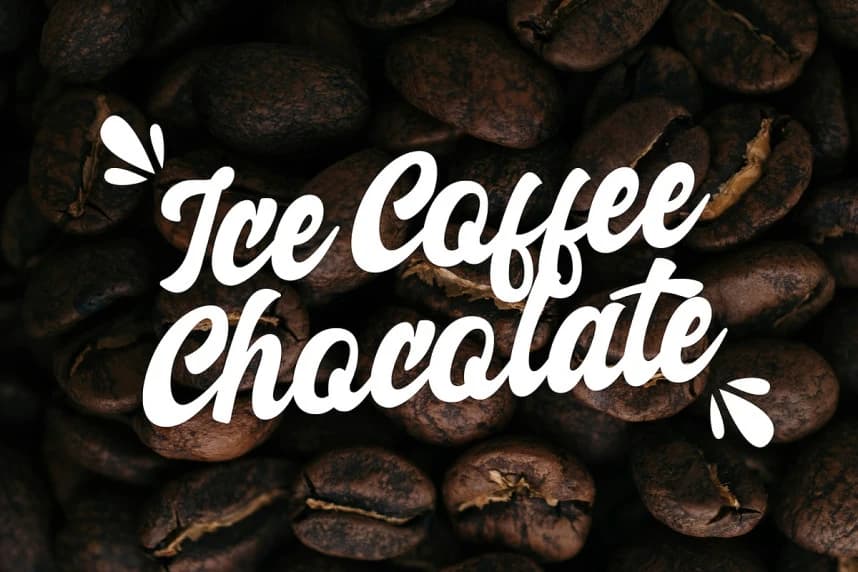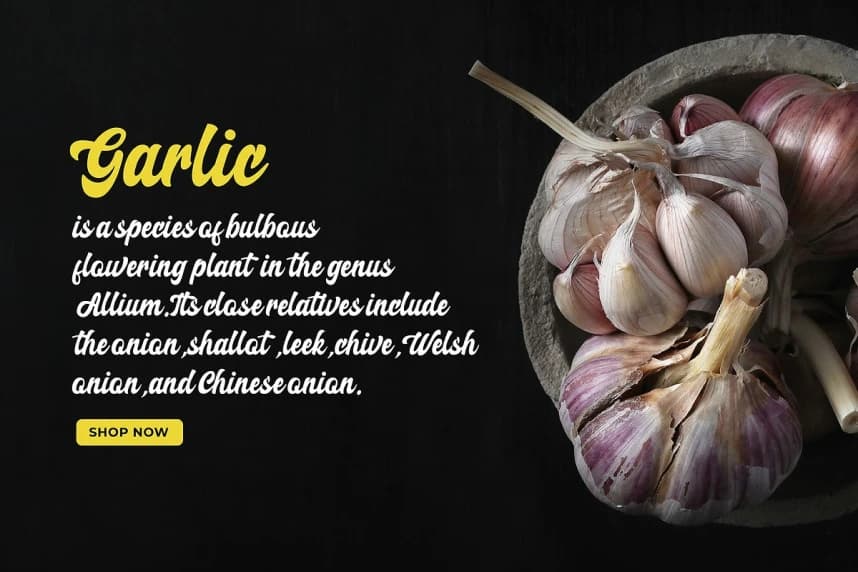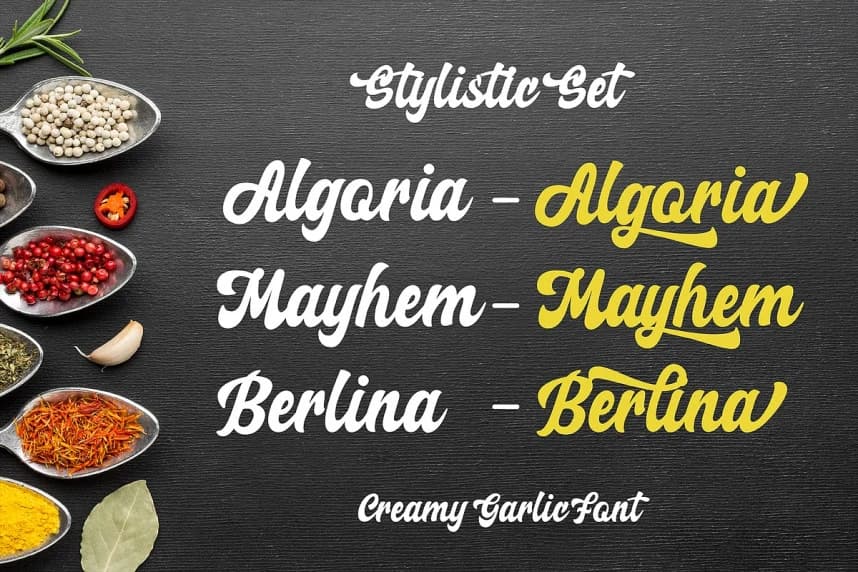
Kremalı Sarımsak Yazı Tipi
Creamy Garlic Font, zevkli ve zarif bir kalligrafik yazı tipidir. Onun zarif çizgileri ve akıcı eğrileri metninize sofistike bir dokunuş katar. Davetiyeler, kartlar veya stil ve çekiciliğin birleşimini gerektiren herhangi bir proje için idealdir.
Creamy Garlic Font, zevkli ve zarif bir kaligrafik el yazısı fontudur. Zarif ve akıcı hatları metninize bir zarafet dokunuşu katar. Davetiyeler, kartlar veya stil ve cazibeyi bir araya getiren herhangi bir proje için mükemmeldir.
Creamy Garlic
Creamy Garlic Script